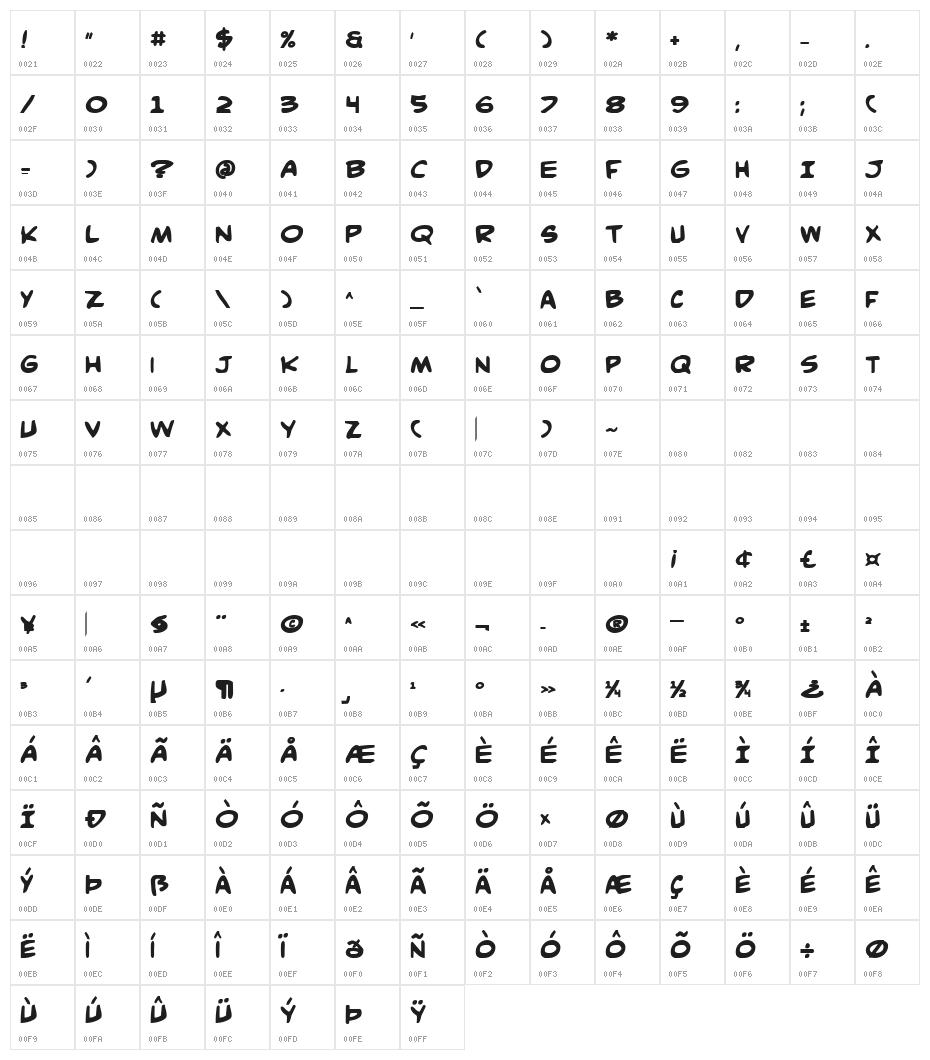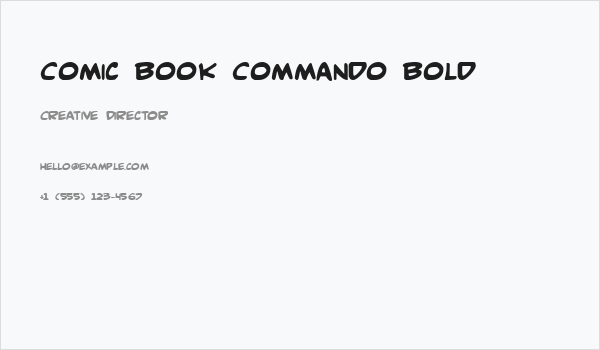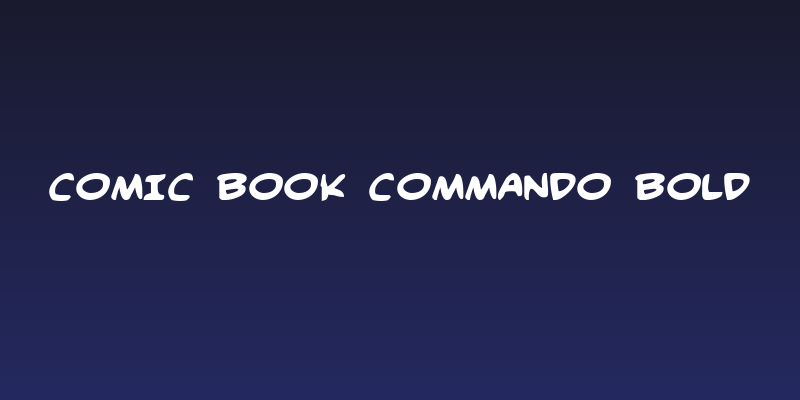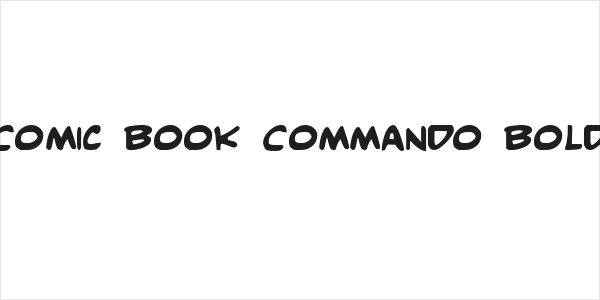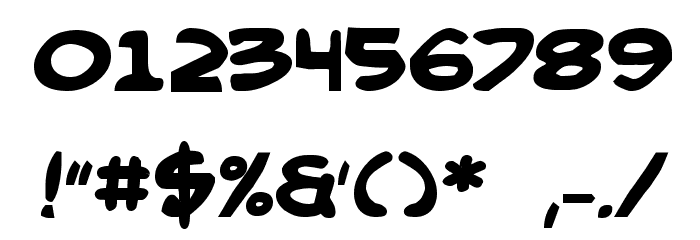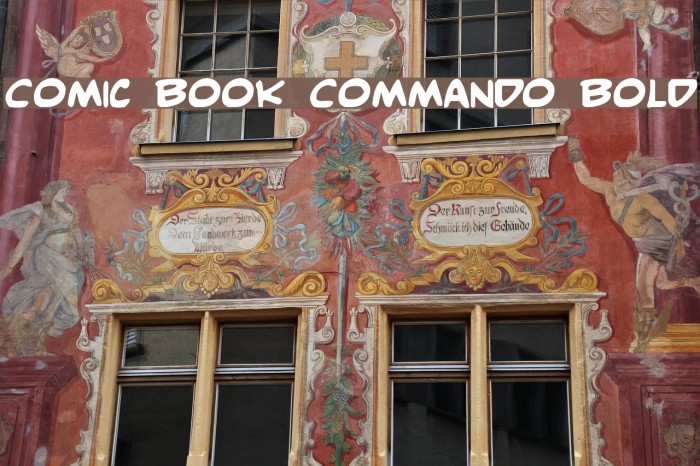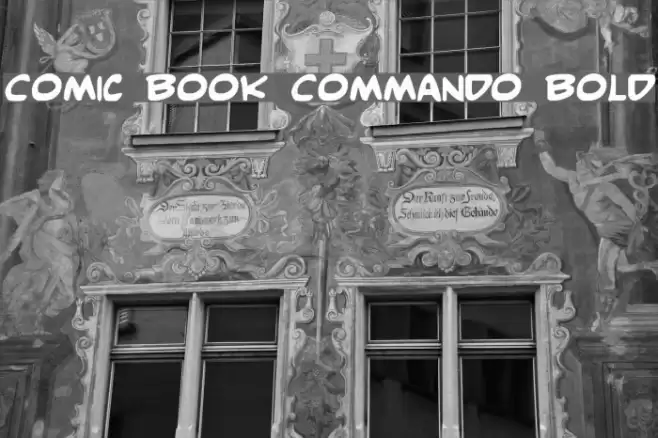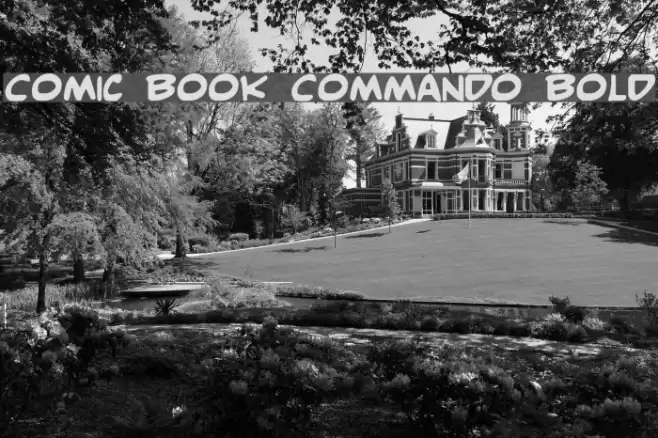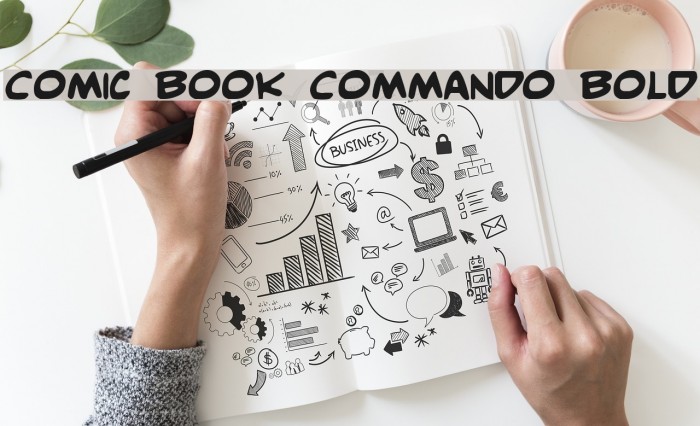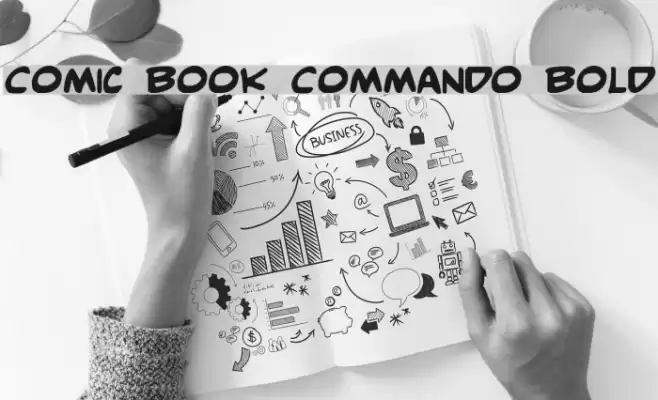
Comic Book Commando Bold Font
| 全体的なスタイル | Playful, Energetic, Comic |
| おすすめプロジェクト | Ideal for comic books, children's books, playful branding, posters, and video game graphics. |